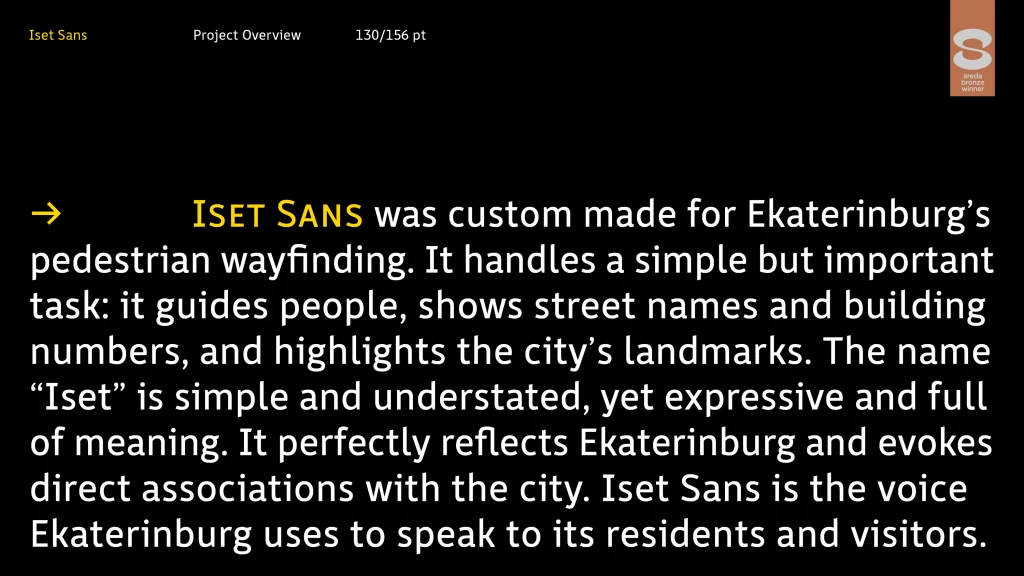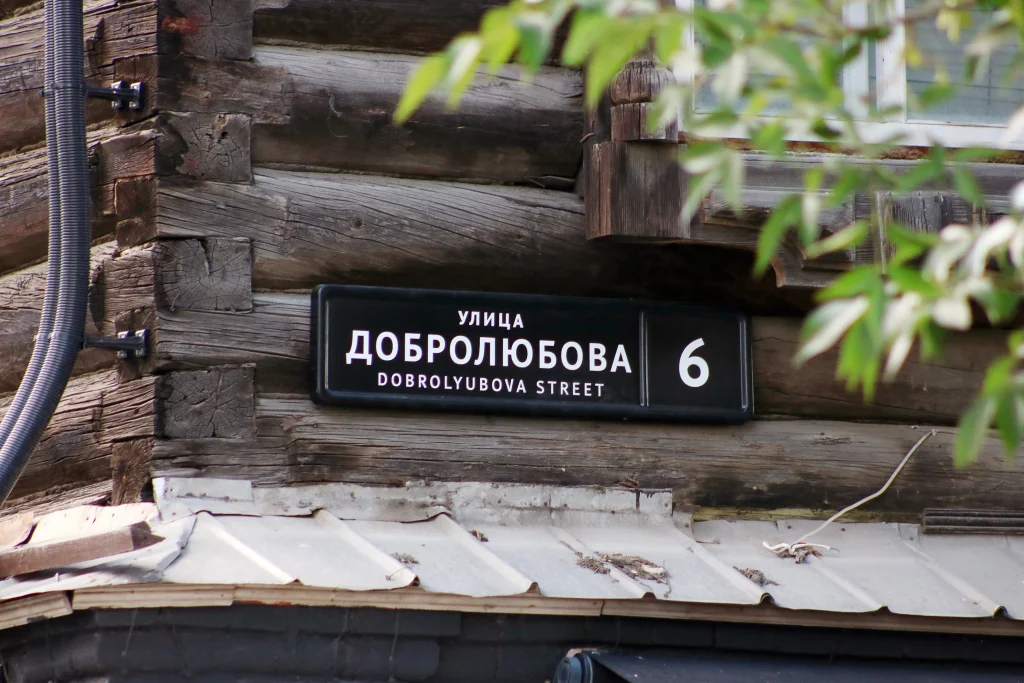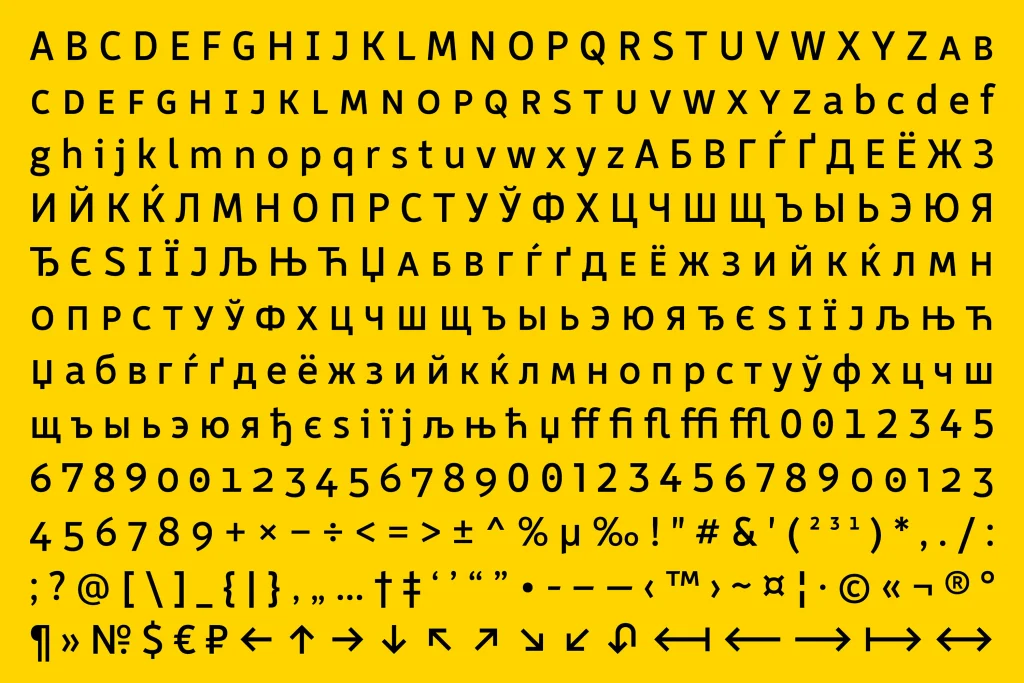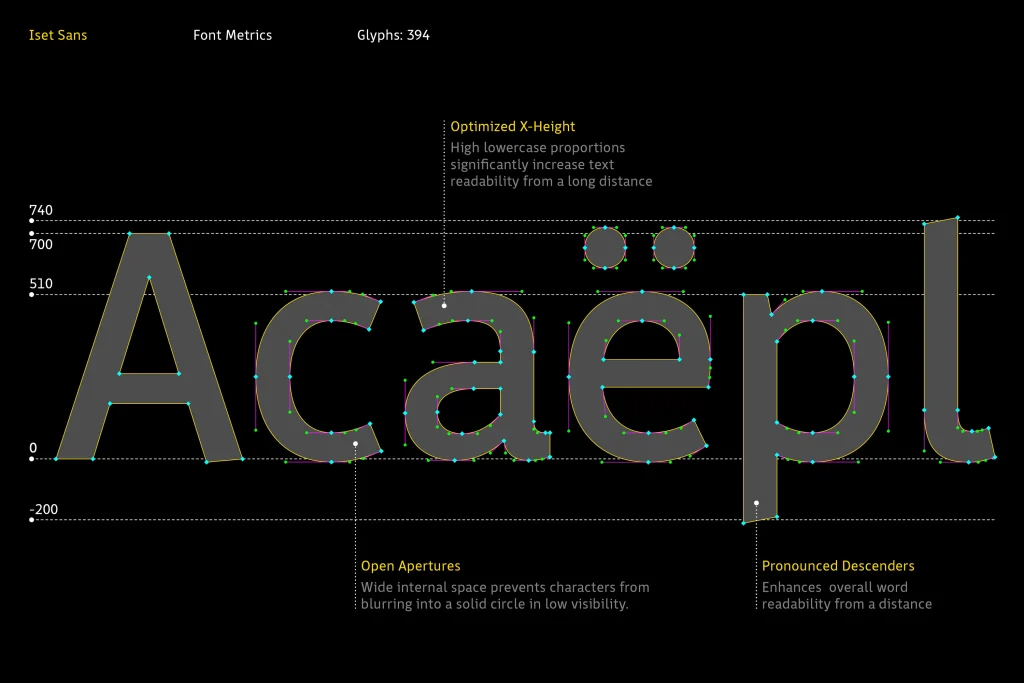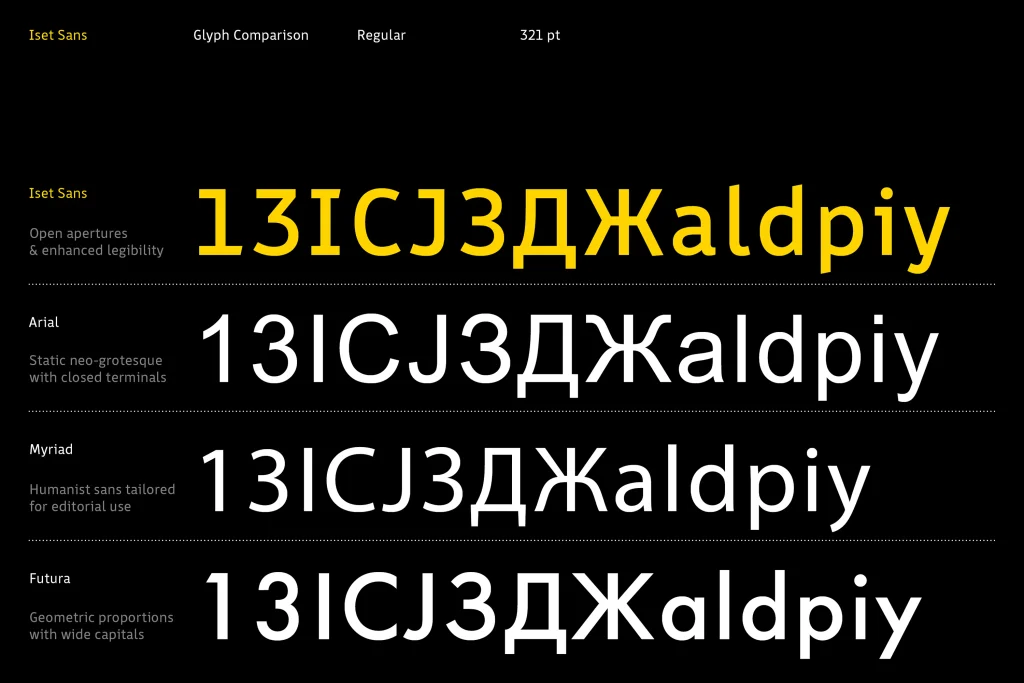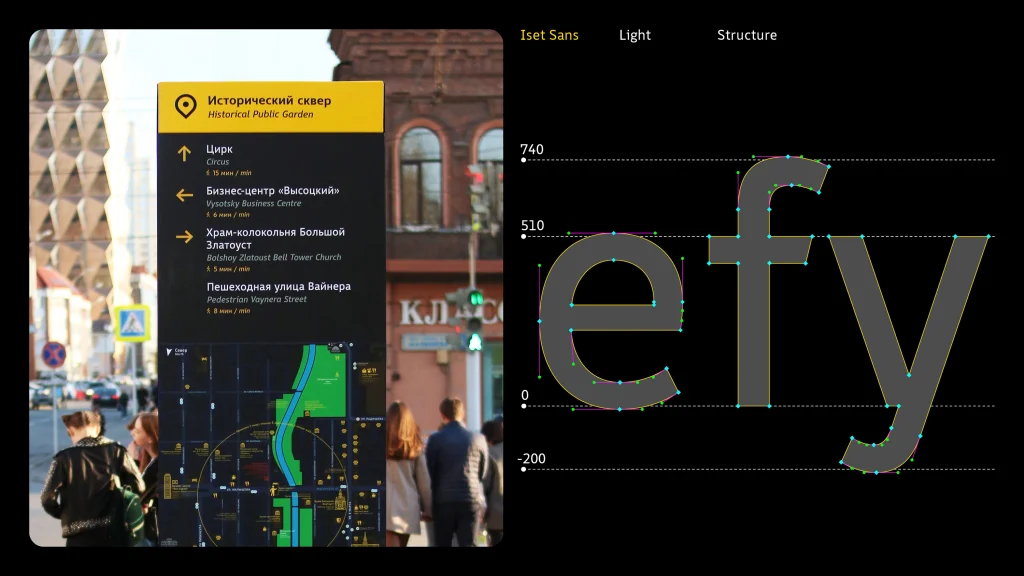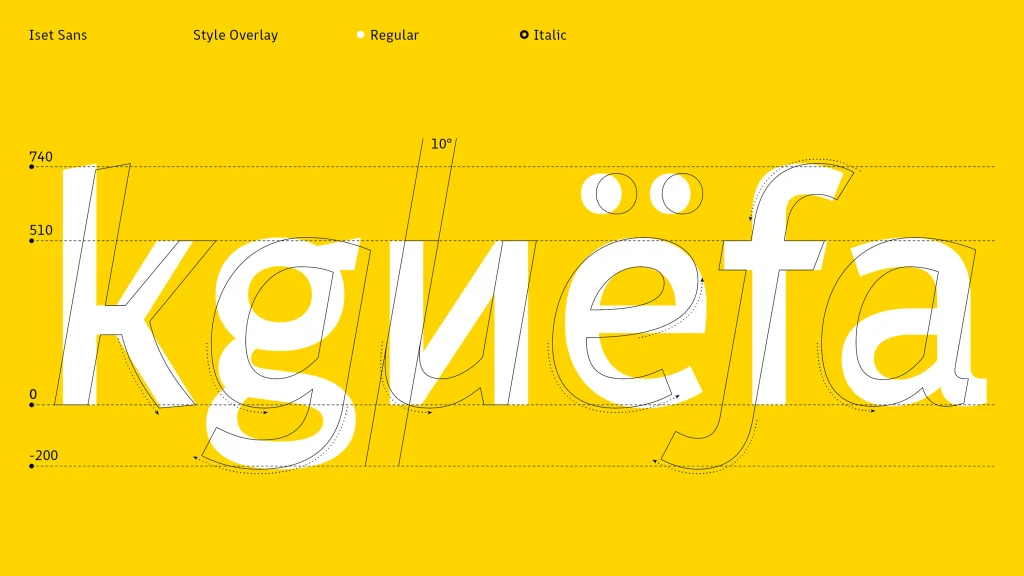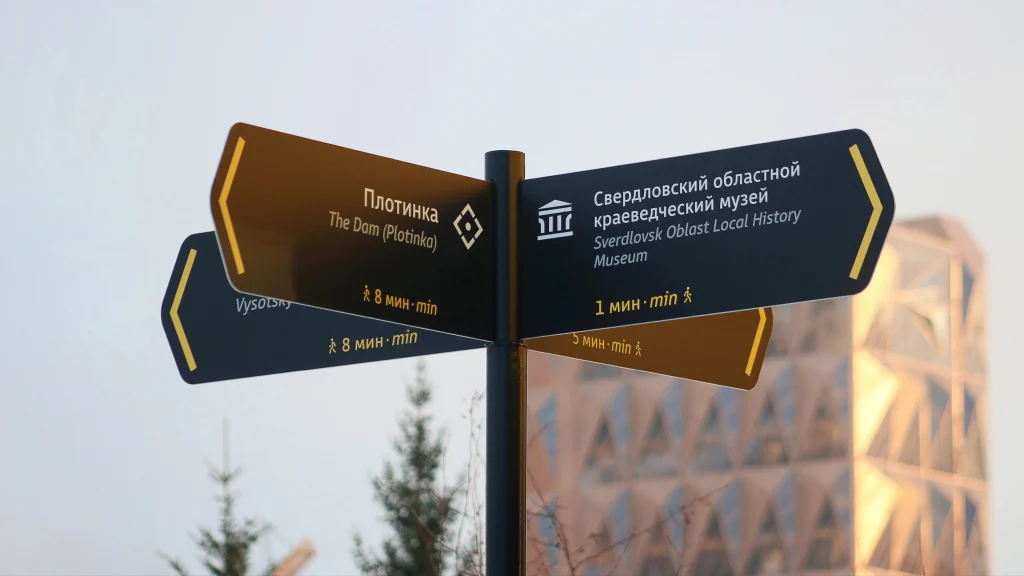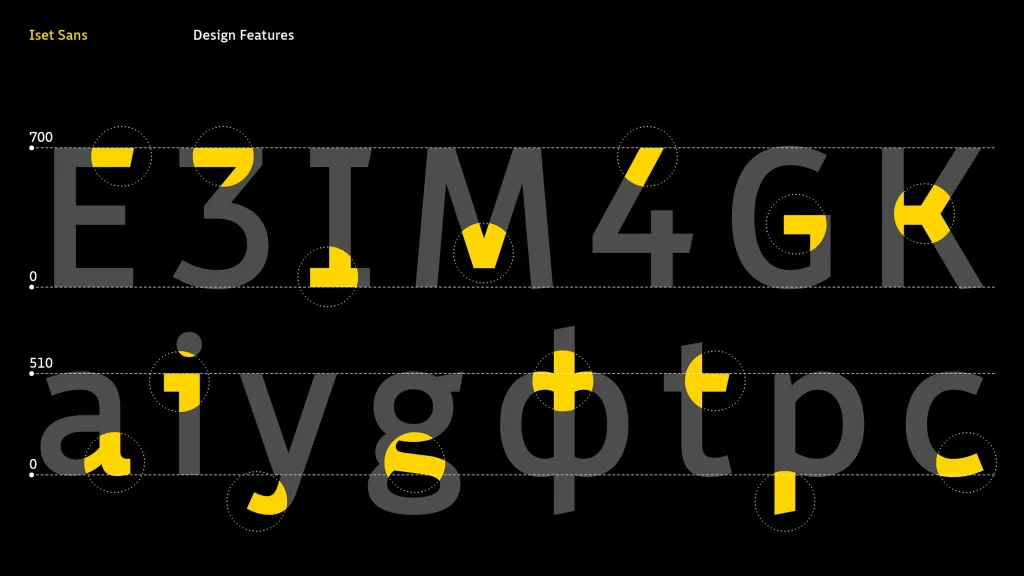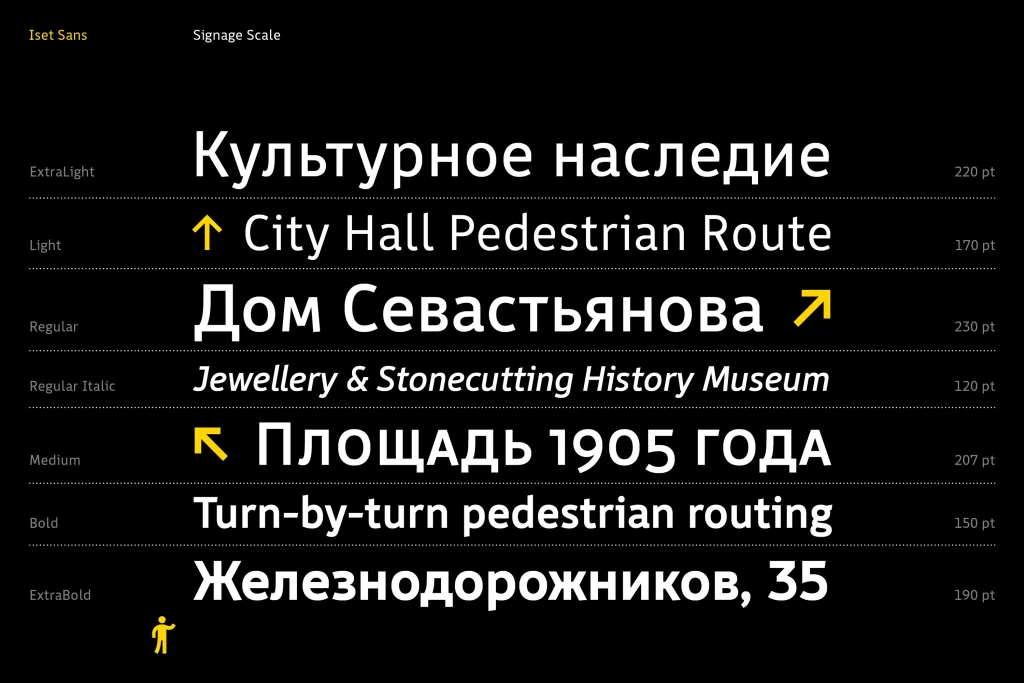
Шрифт Iset Sans разработан специально для пешеходной навигации и системы городских указателей Екатеринбурга. Он выполняет важную задачу: указывает направления маршрутов, сообщает названия улиц, номера домов и рассказывает о достопримечательностях города. Название «Исеть» простое и сдержанное, но при этом ёмкое и выразительное; оно точно передаёт дух Екатеринбурга и вызывает прямые ассоциации с городом. Iset Sans — голос, которым Екатеринбург обращается к жителям и гостям.
Это открытый, динамичный гротеск с ясными, чуть зауженными пропорциями знаков и характерными конструктивными деталями в прописных и строчных глифах. Так обеспечивается быстрое и безошибочное считывание текста на расстоянии. Семейство включает шесть начертаний: ExtraLight, Light, Regular, Medium, Bold и ExtraBold, а также Regular Italic. Оптимизированная высота строчных знаков в сочетании со сбалансированными выносными элементами позволяет компактно размещать текст по вертикали. В то же время униширинная система (Uniwidth) сохраняет горизонтальную консистентность, обеспечивая одинаковую длину строки во всех начертаниях.
В городской навигации Екатеринбурга активно используется тёмный фон (стелы, указатели, информационные таблички). Поэтому Iset Sans спроектирован чуть более плотным, чем обычные текстовые гарнитуры, что компенсирует эффект световой иррадиации и позволяет легко считывать знаки на тёмных поверхностях. Знаковый состав каждого начертания включает капитель, пропорциональные, табулярные и минускульные цифры, а также регистрозависимые формы. Набор дополнен функциональными лигатурами, различными типами пробелов для вёрстки и развитой системой навигационных стрелок. Эти решения обеспечивают универсальность применения гарнитуры на адресных табличках, стелах, указателях и информационных панелях, а также в общественном транспорте, сохраняя единообразие визуальной идентификации города.
Iset Sans получил бронзу в категории «Заказной шрифт» на фестивале Нового дизайна «Среда» 2024.